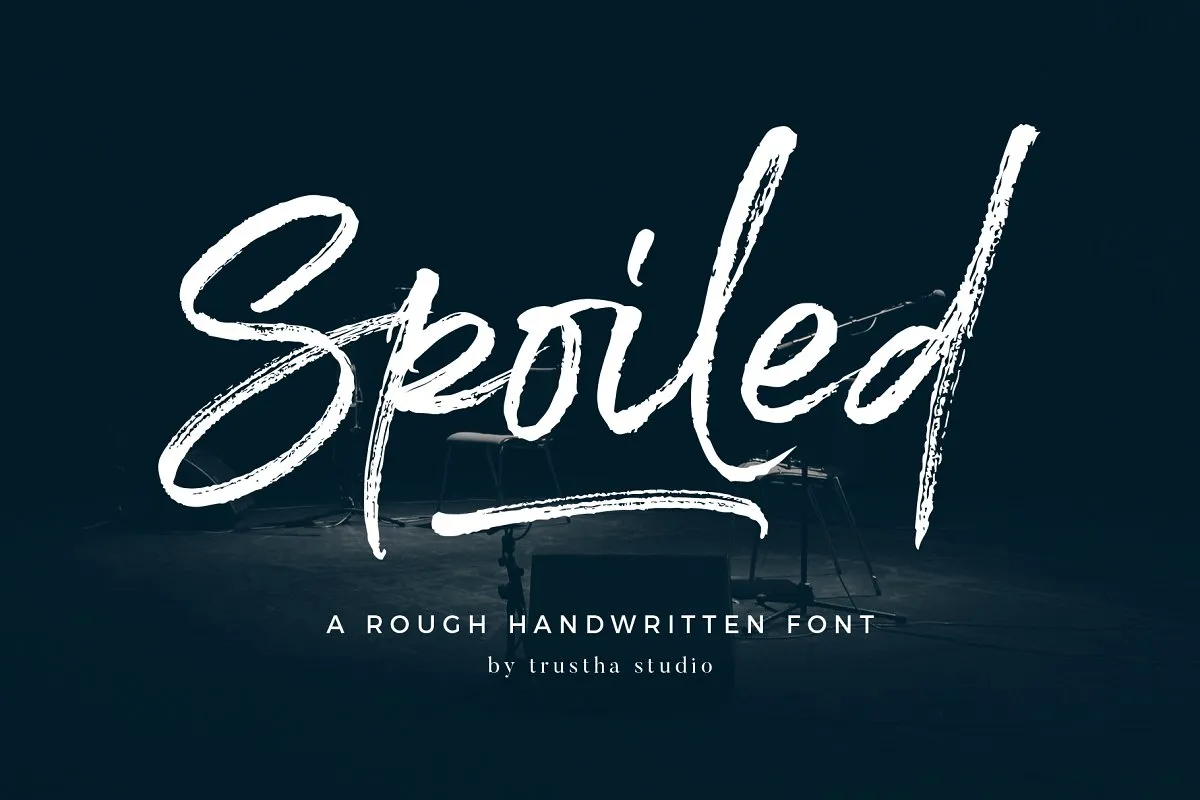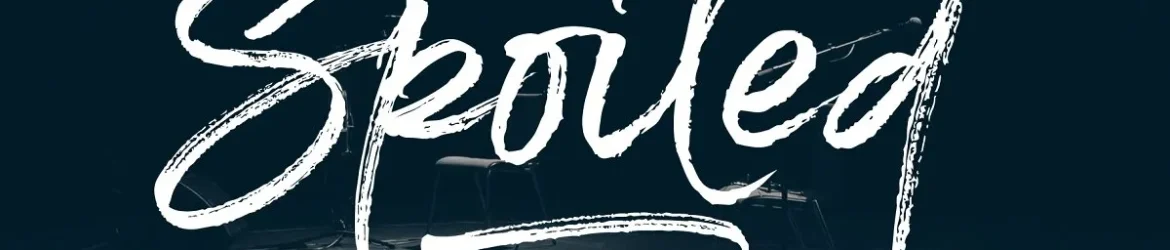
Olá amigo. Aqui tem uma nova linha de estilo de pincel. Adicione agora à sua coleção de fuentes. Introduzimos a Fórmula Descuidada . A Descuidada é um tipo handwritten com aparência rústica. Tem um estilo natural que torna-a perfeita para branding, propaganda, design de painéis, logotipos, capas de livros, revistas, embalagens, cabeçalhos de sites, cartões de boas-vindas, designs de roupa, merchandising, campanhas fashion, anúncios de newsletter e capas de álbuns. E muito mais.